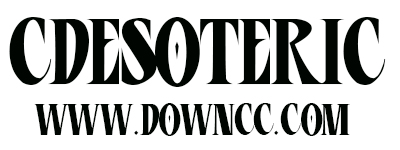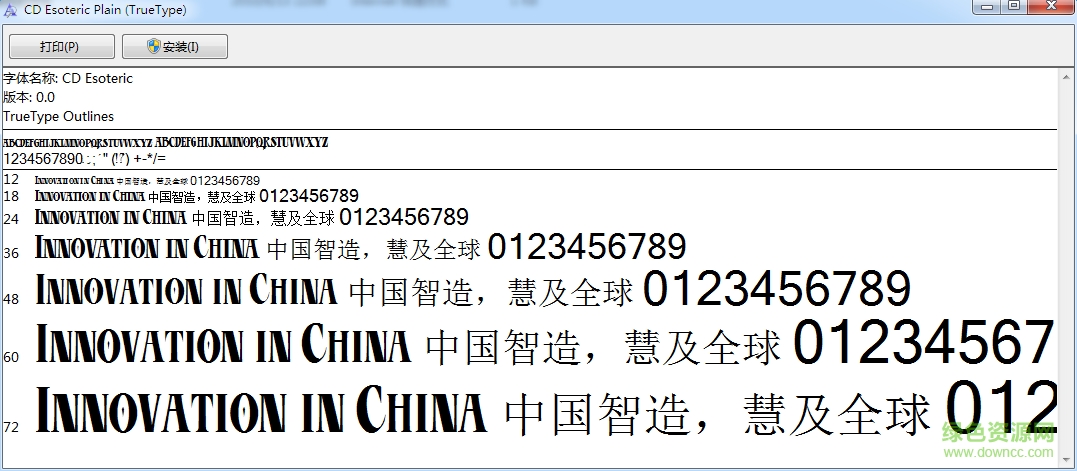
cdesoteric字體相比較其他英文字體來(lái)說(shuō)還算是比較規(guī)范的,這款字體輸出的英文看起來(lái)很美觀整潔。多用于印刷設(shè)計(jì)、廣告設(shè)計(jì)、海報(bào)設(shè)計(jì)等。歡迎下載使用。
Cdesoteric字體是一款字形鮮明的英文字體,線條比較粗,看上去非常的醒目,至于安裝方法按照指示操作就可以使用到了!快來(lái)綠色資源網(wǎng)下載使用吧。